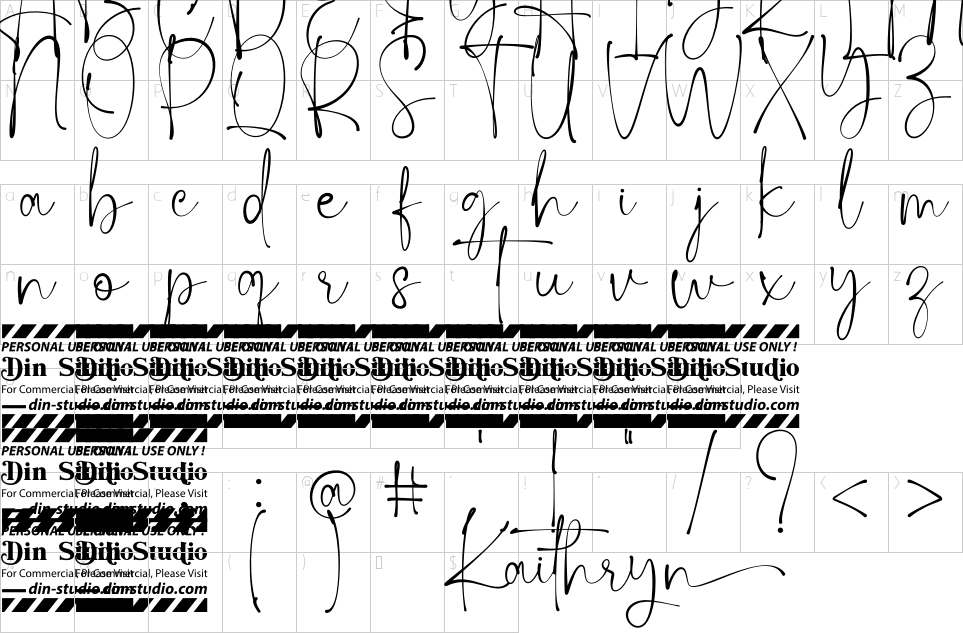
Kaithryn Font – Download Grátis
Descubra a elegância e a simplicidade da Kaithryn Font, uma fonte gratuita que oferece uma experiência gráfica agradável para seus projetos. Desenvolvida pela Din Studio, essa fonte vem em versões para Windows e Mac, sendo uma opção versátil para designers e criativos. Com seu design limpo e fácil de ler, a Kaithryn Font é ideal para uso em textos, logos, flyers ou qualquer outro projeto visual que requer uma face elegante e moderna. Seu design minimalista também a torna uma ótima escolha para quem busca uma fonte que se destaca sem desviar a atenção do conteúdo. A Kaithryn Font já foi baixada 3.588 vezes, evidenciando seu valor e popularidade. Instale-a em seu computador hoje e experimente o seu estilo único.